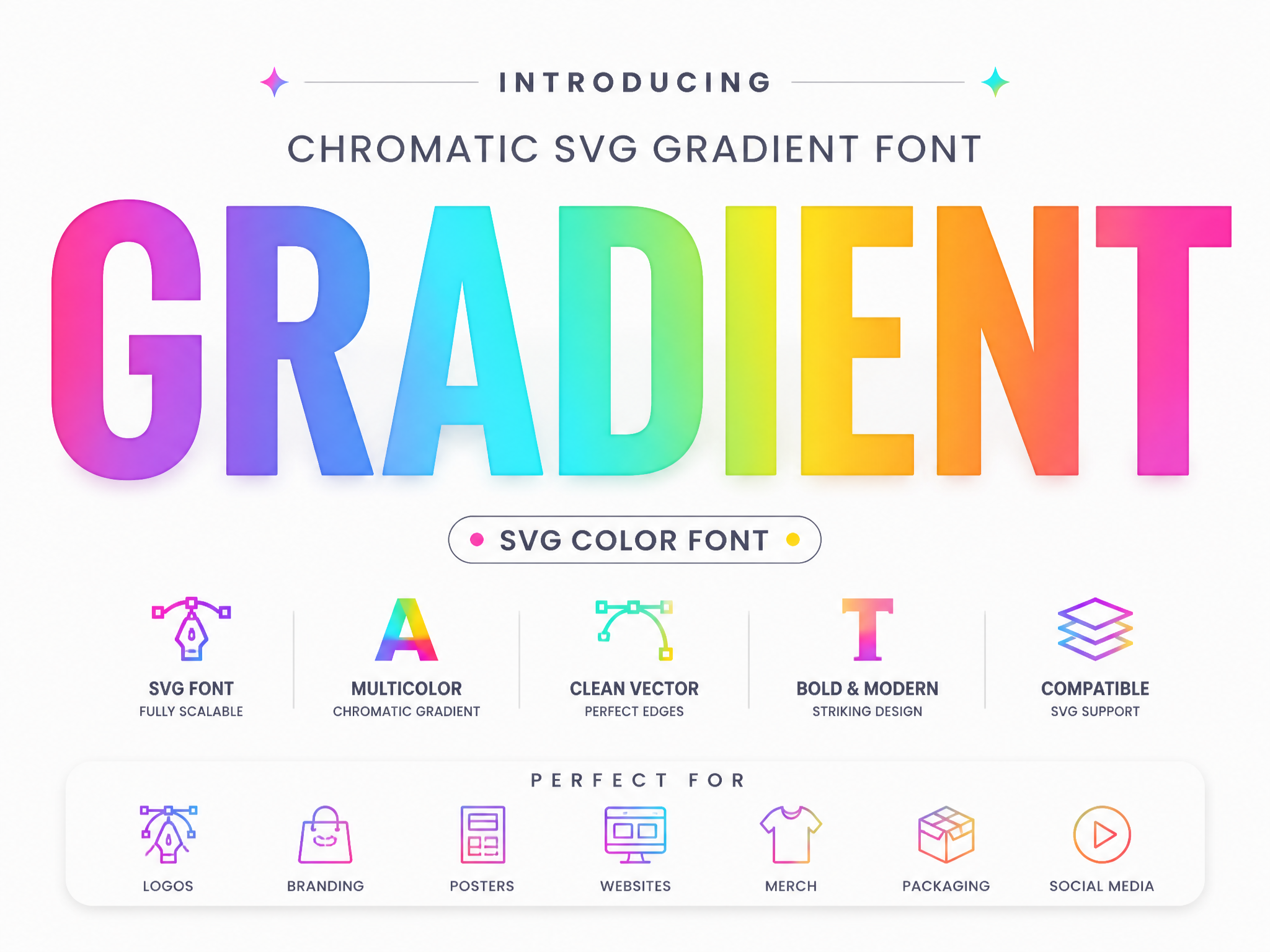
Renkli & SVG Gradient Font Paketi; her harfin içine canlı renk geçişleri (gradient) işlenmiş, dikkat çekici bir SVG font koleksiyonudur. Sosyal medya görselleri, YouTube küçük resimleri ve dijital içerik üretimi için mükemmeldir. Paket; gökkuşağı, pastel ve neon olmak üç farklı renk temasında alternatif karakter setleri sunar. SVG destekli uygulamalarda (Illustrator, Photoshop) çok renkli görünümü otomatik aktive olur; diğer uygulamalarda standart renk olarak görünür. OTF ve yüksek çözünürlüklü PNG formatlarında teslim edilir; ticari kullanıma uygundur.
Renkli & SVG Gradient Font Paketi